手写体是一种用硬笔、软笔纯手工写出来的文字,手写体文字代表了中国汉字文化的精髓。手写体的大小不一、风格各异是一种有“温度”的字体。手写体近年来已经得到了进一步的开发,时常应用在设计领域大放异彩。
汉标手写巨黑:作者运用粗毛笔大胆书写,笔画清朗有劲,简约美观。虽为基本等线黑体,却具有传统中国书法的气韵,字字皆生动有神。具张力的曲线,加上精准的几何线条结构,字形清晰易于图片识别字体。汉标粗黑体稳重的风格应用于信息排印与显示实为上佳选择。
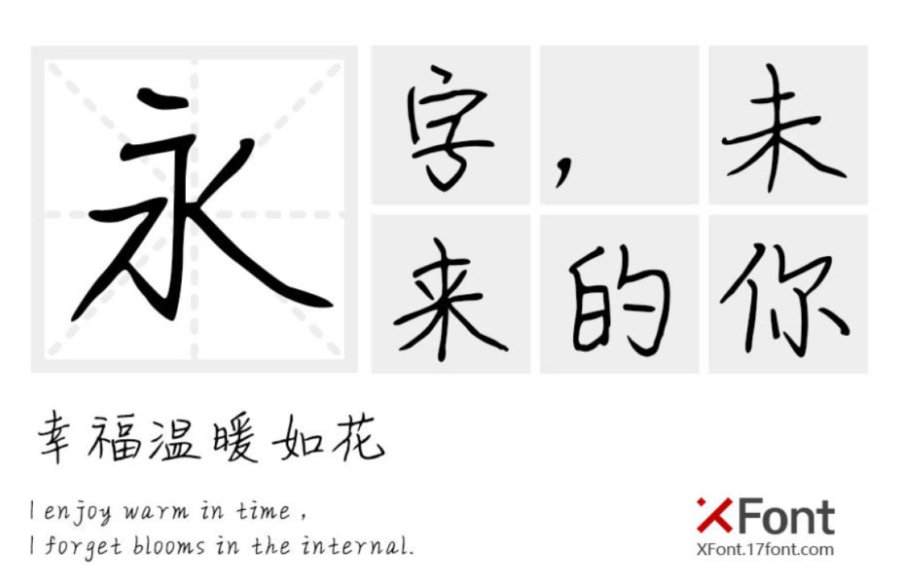
将故事写成我们:这是一款带有楷书书写风格的手写体,笔画的轻重变化、停顿与连带处理的精巧细致。字体的布局互相呼应,结构合理。适用于文艺书刊、杂志的封面及正文设计、广告标语、屏幕显示、影视等领域。
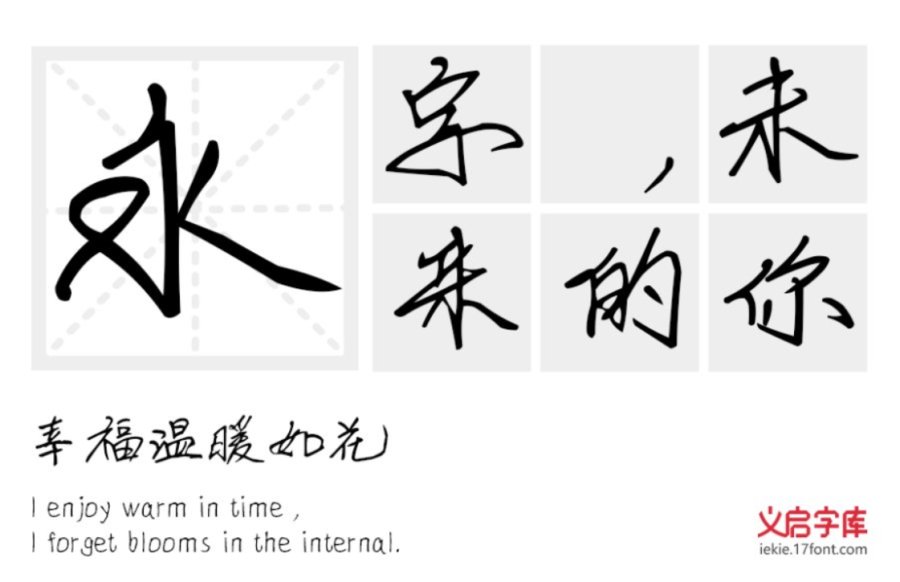
义启手写体:这款字体以女孩笔迹为基础,融入天然、爽朗、以拙为巧等元素。用笔洒脱自然,映带婉转但又不刻意雕饰。适用于书籍、杂志的标题及正文、书法类作品、影视、包装设计、屏幕显示、社交网络的个性化用字等领域。